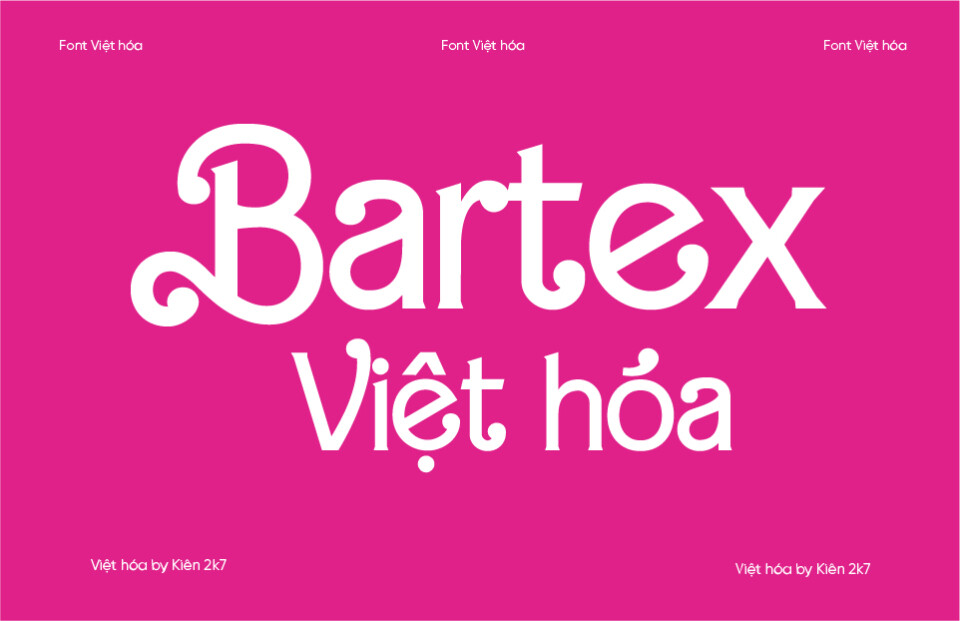
Giới thiệu về Font Việt hóa KK7 Bartex
Font Việt hóa KK7 Bartex là một trong những bộ phông chữ độc đáo nhất hiện nay, mang phong cách thiết kế hiện đại pha chút phá cách. Khi tìm kiếm một Font Miễn Phí để làm mới các ấn phẩm truyền thông, bộ font này chắc chắn sẽ là lựa chọn hàng đầu. Với cấu trúc đường nét rõ ràng và cá tính, bộ font không chỉ phù hợp cho các poster sự kiện mà còn cực kỳ hữu ích cho các dự án sáng tạo của học sinh. Việc sở hữu một phông chữ đã được việt hóa hoàn chỉnh giúp người dùng dễ dàng gõ tiếng Việt có dấu mà không lo gặp lỗi hiển thị hay mất nét chữ.
Đặc điểm nổi bật của Font Việt hóa KK7 Bartex
Phong cách thiết kế sáng tạo
Bộ phông chữ này gây ấn tượng mạnh nhờ vào các nét cắt gọt tinh tế và độ dày vừa phải. Điều này giúp văn bản trở nên dễ đọc nhưng vẫn giữ được sự thu hút cần thiết. Đối với các bạn học sinh đang thực hiện báo tường hoặc trình chiếu slide, phông chữ này giúp bài làm trở nên chuyên nghiệp và bắt mắt hơn hẳn các font mặc định thông thường.
Khả năng ứng dụng linh hoạt
Bạn có thể sử dụng bộ font này trong nhiều trường hợp khác nhau. Từ việc thiết kế logo câu lạc bộ, làm thiệp mời cho đến việc trang trí các tiêu đề bài học. Sự linh hoạt của nó cho phép người dùng kết hợp với nhiều màu sắc và nền tảng thiết kế khác nhau như Canva, Photoshop hay PowerPoint một cách mượt mà.
Để đạt hiệu quả thẩm mỹ cao nhất, bạn nên ưu tiên sử dụng phông chữ này cho các tiêu đề lớn hoặc các câu trích dẫn ngắn. Tránh việc dùng cho các đoạn văn dài để đảm bảo tính dễ đọc. Khi tải về, bạn chỉ cần giải nén và cài đặt trực tiếp vào hệ điều hành để bắt đầu sáng tạo. Chúc các bạn có những tác phẩm thiết kế thật ấn tượng và độc đáo cùng với Font Miễn Phí, Font Việt Hóa, Font Việt hóa KK7 Bartex đầy tiện lợi này.